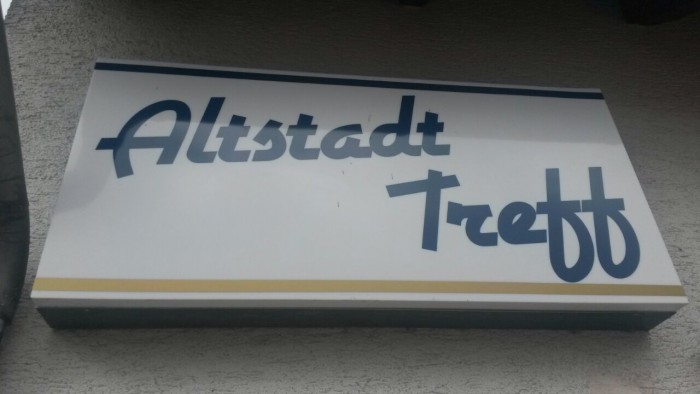
Ich suche folgende Schrift (Altstadt-Treff)
kann mir jemand sagen wie die folgende Schrift heißt?
war, oder ist auch im CorelDraw-Schriftenpaket enthalten, da Werbebeschrifter oft Coreldraw nutzen sind ves oft auch Schriften aus diesem Paket. Daher auch die deutlich überzählige Verwendung der Avant Garde auf Ladenschildern und Autobeschriftungen in den 1990ern, da hier das die Corel-Standardschrift war, die bei wahl des Schriftwerkzeuges zuerst kam.